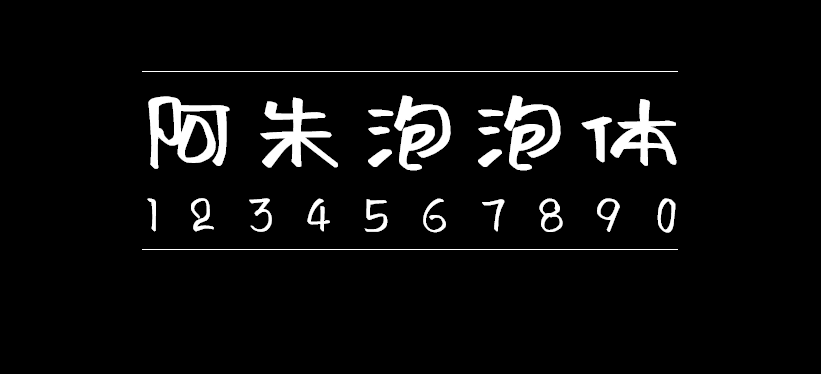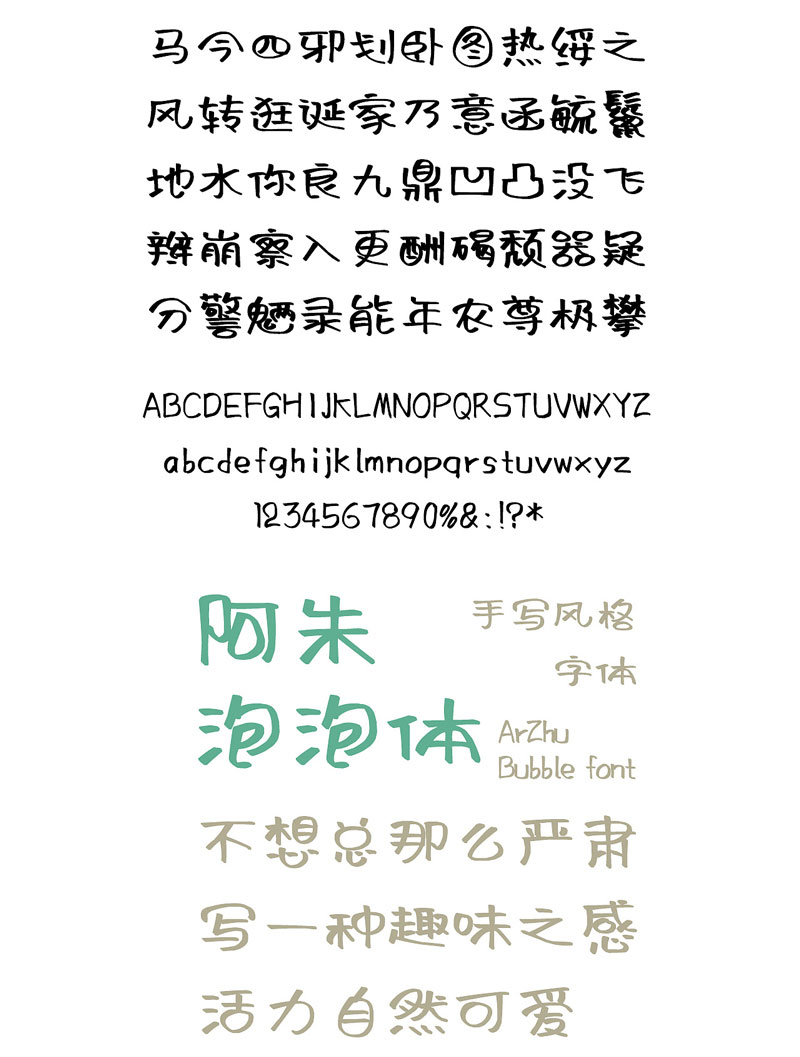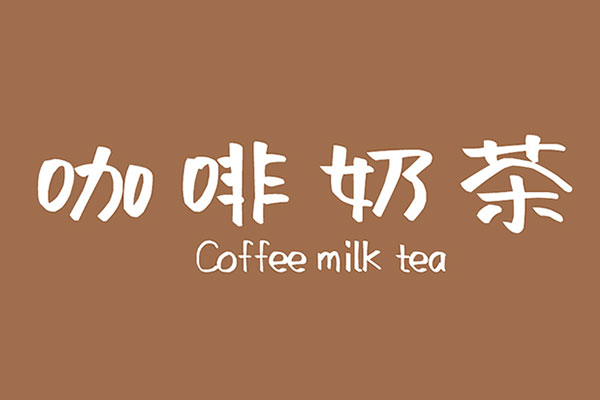
阿朱泡泡体
阿朱泡泡体发布于2019年的光棍节,这是一款字体书写笔画随意放松,富于变化,充满卡通趣味极富装饰色彩,特别是口型偏旁由“泡泡”组成,使字体充满青春活力风格鲜明,特点突出,能够适用于艺术设计、包装印刷、签名设计、图形设计等领域,免费授权全社会使用(包括免费商用). 阿朱泡泡体基于GB2312-80字符集标准,共收录汉字6763个汉字和数百个符号。